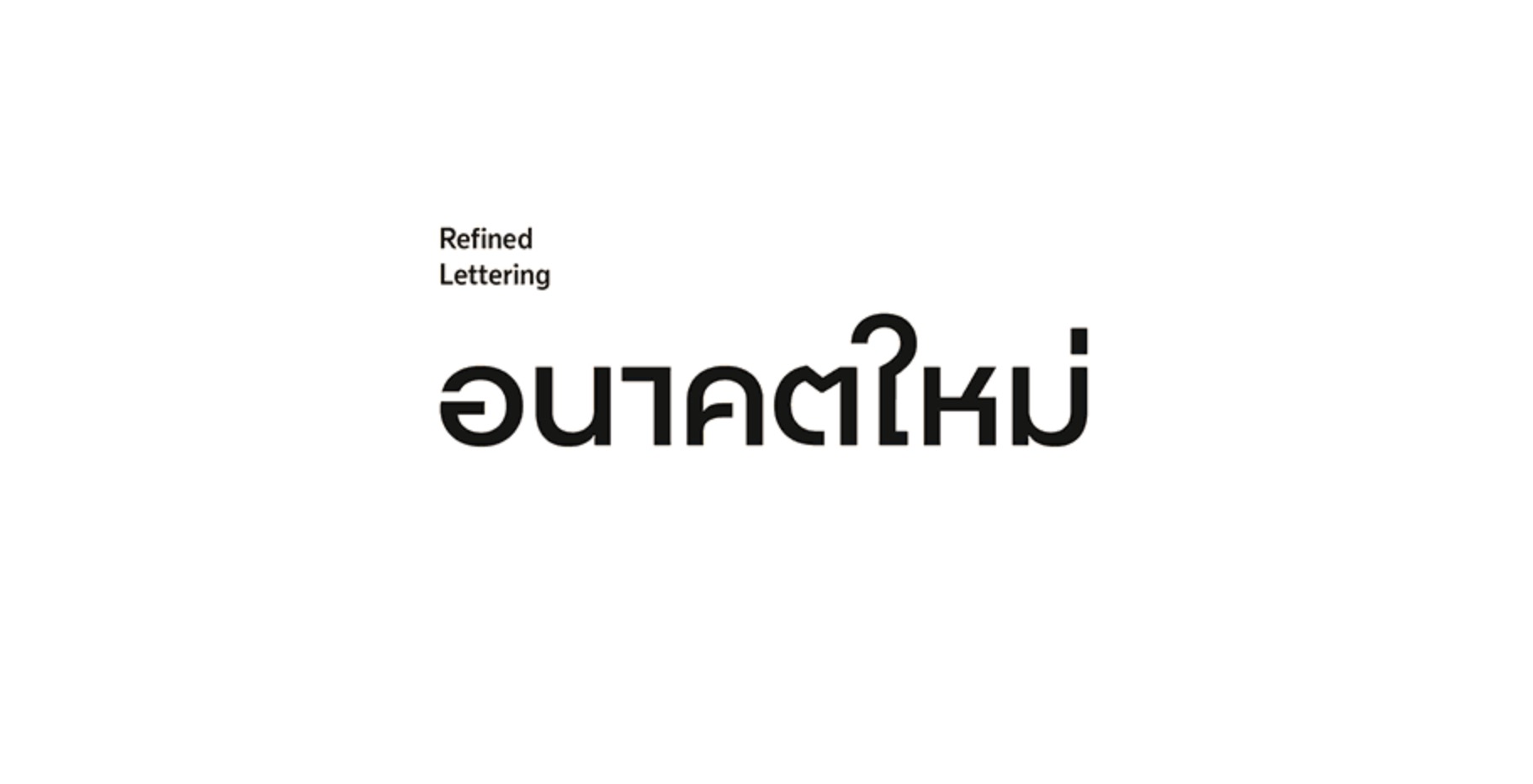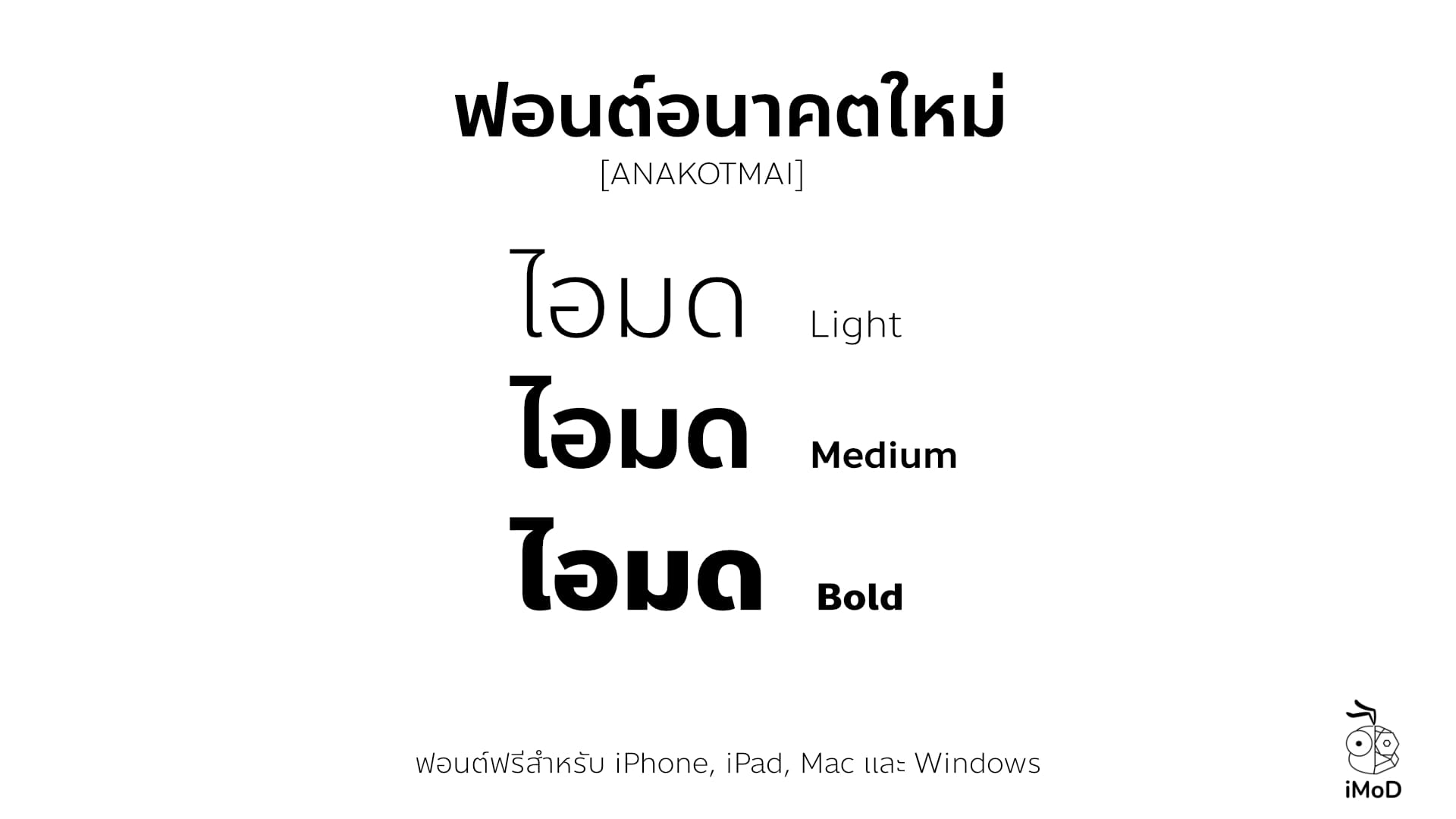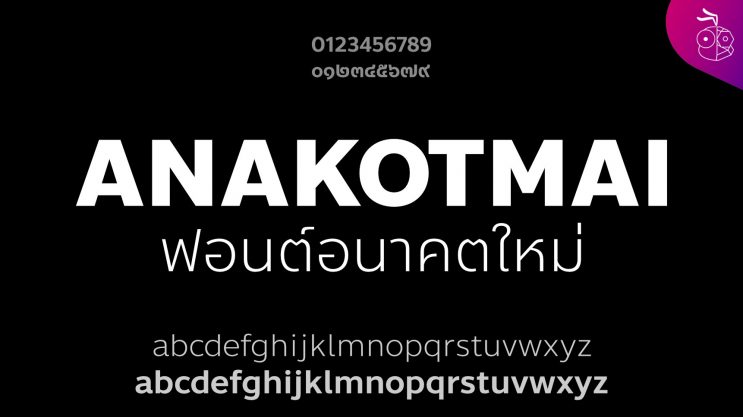
ทราบข่าวว่ามีฟอนต์แจกฟรีเป็นฟอนต์ซึ่งไม่ได้มามีในปัจจุบันเพราะเป็นฟอนต์มาจาก “อนาคต(ใหม่)” ที่ได้รับการปรับปรุงจากเวอร์ชันเดิมให้ดีขึ้นโดยทีมงานมืออาชีพอย่าง “คัดสรรดีมาก” เจ้าเดียวกันกับที่ทำฟอนต์ “สุขุมวิท” ที่ใช้งานใน iOS 7 รอบนี้ฟอนต์อนาคตใหม่ (Anakotmai) เปิดให้ดาวน์โหลดไปใช้งานกันได้ฟรี เชิญโหลดได้เลยทั้ง iOS, macOS และ Windows
ฟอนต์ “อนาคตใหม่” สำหรับที่มาที่ไปเป็นอย่างไรนั้นสามารถอ่านได้ที่นี่ ส่วนหน้าที่ของทีมงานก็แค่เพียงนำข่าวมาบอกต่อซึ่งฟอนต์นี้ติดตั้งแล้วใช้งานได้ดีและสวยงาม เรียบง่าย อ่านได้ดีเลยนำมาเผยแพร่ให้ดาวน์โหลดไปใช้กัน (ขอความกรุณาอย่าโยงเข้าการเมืองนะครับบอกก่อนเลย)
ฟอนต์มีให้เลือกใช้ 3 น้ำหนัก ได้แก่ Light, Medium และ Bold